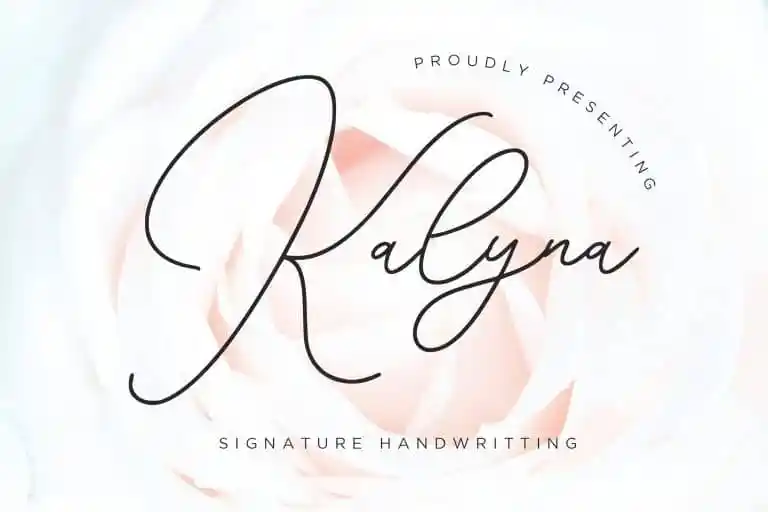
Kalyna Handwritten Font – Download Grátis
Kalyna Handwritten Font é uma elegante tipografia frondesada criada por Creatype Studio, com ligaturas bonitas, elementos especiais de caracteres e suporte multilíngue. Esta fonte ideal para projetos de marca, logotipos, designs de casamentos, posts nas redes sociais, anúncios, embalagens de produtos, design de produtos, rótulos, fotografia, marcadores d’água, convites e materiais de assinatura. Kalyna Handwritten Font é uma escolha perfeita para qualquer projeto que exige um toque de escrita frondesada. A sua beleza e simplicidade fazem dela um aliado ideal em várias aplicações gráficas.